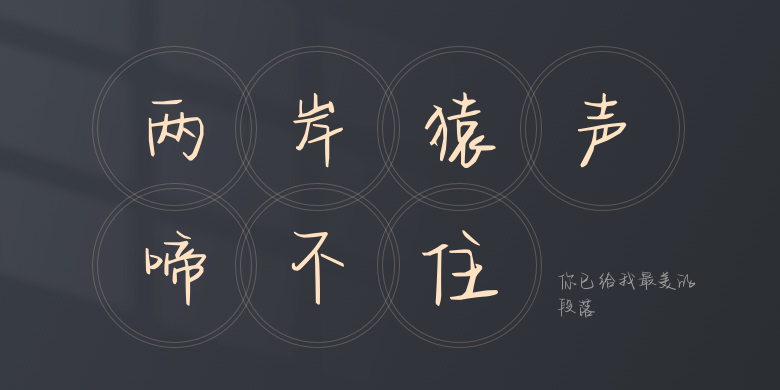
你已给我最美的段落
你已给我最美的段落,这款字体结构工整、笔画清晰,兼顾美观与易读性,适用于标题、正文、海报、包装、LOGO 等多种场景。字形优雅稳定,风格百搭耐看,适配日常排版与创意设计,让文字呈现更舒适、更具质感。你已给我最美的段落一笔一画,皆是细节,以均衡的比例、流畅的线条打造舒适视觉体验,字形端正大气,风格简约现代。无论是商业设计、品牌宣传还是日常排版,都能轻松驾驭,让文字更有格调与力量。你已给我最美的段落字体下载。